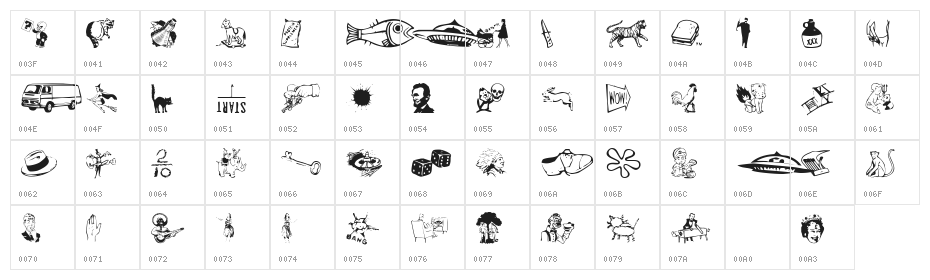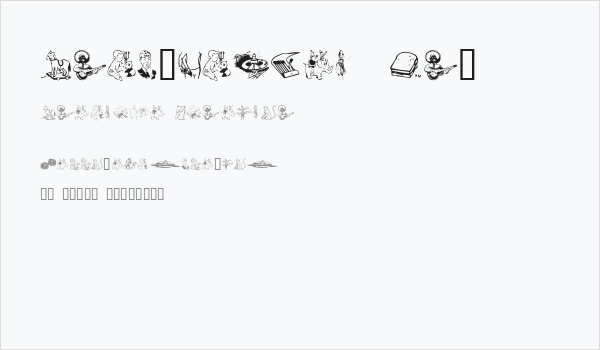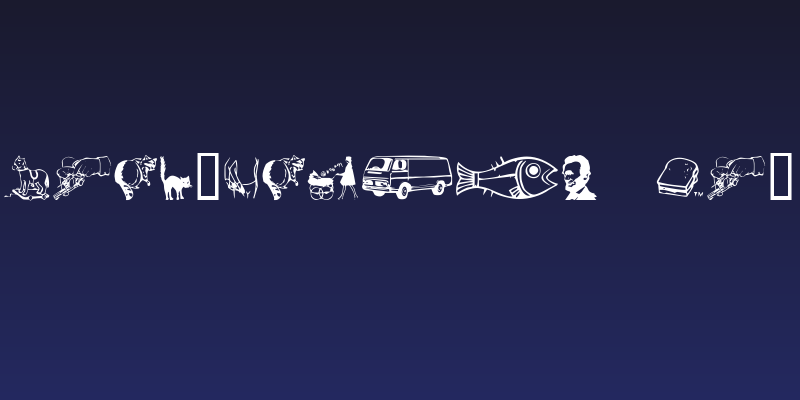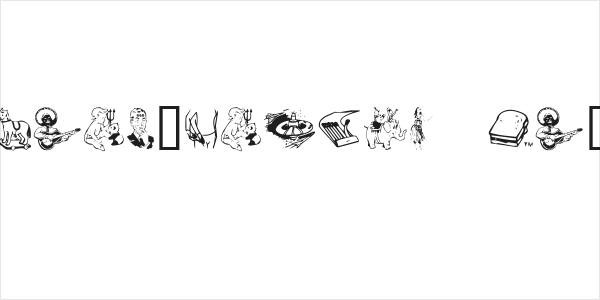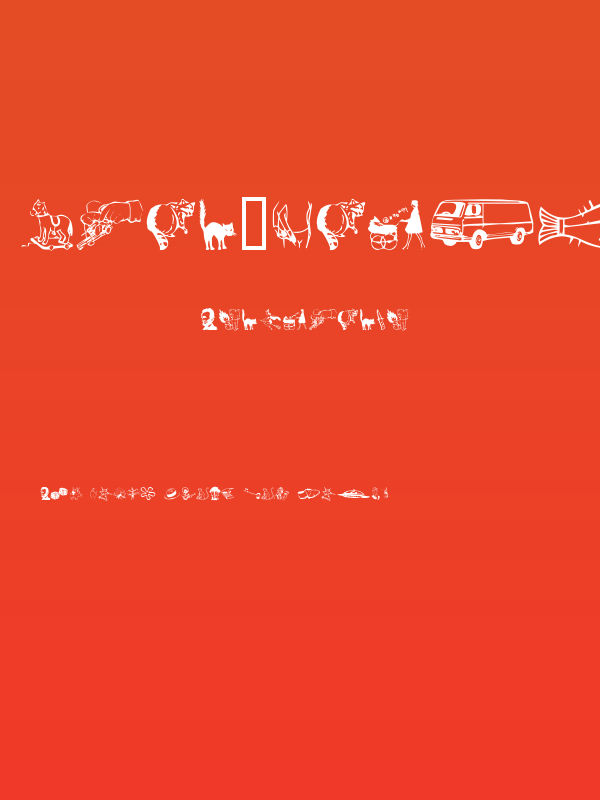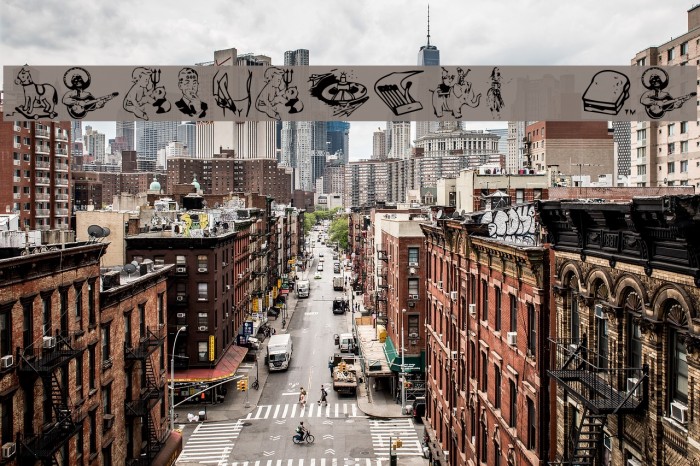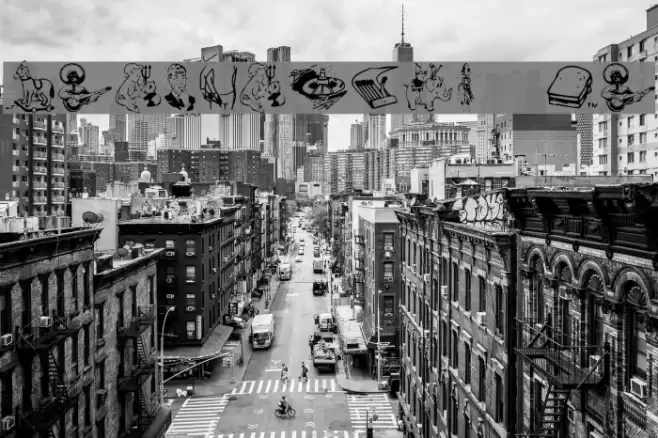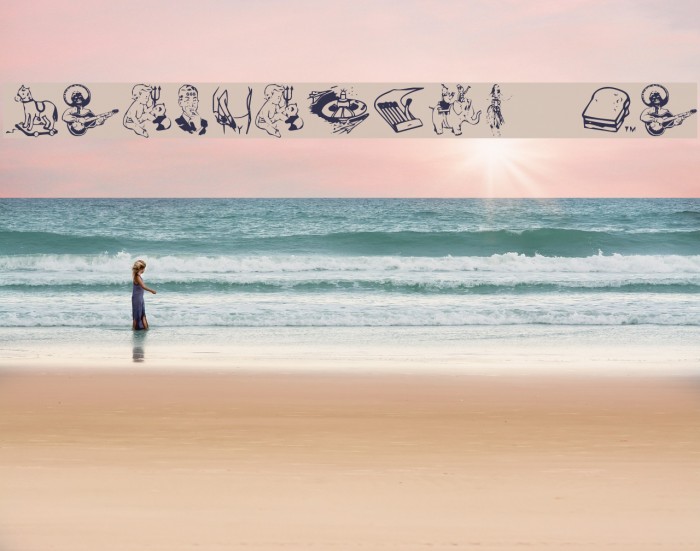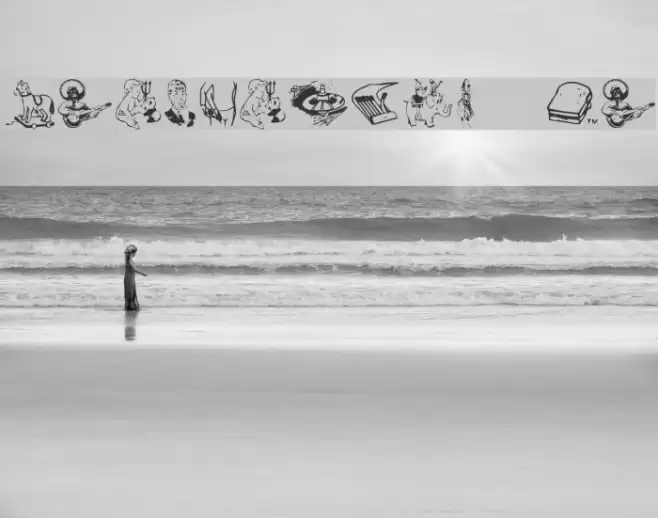
Crap*Magnet Jr. Font
| 全体的なスタイル | Decorative, Whimsical, Comic |
| 用途 | Illustrative elements, Decorative accents, Themed graphics |
| おすすめプロジェクト | Children's books, comic strips, party invitations, playful branding, educational materials, creative posters. |